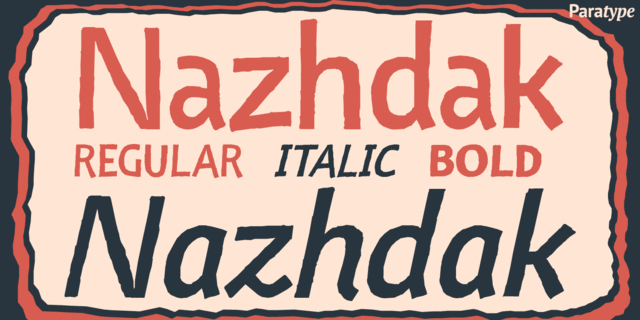
Наждак - рукописный гротеск в трех начертаниях, нарисованный фломастером и впоследствии оцифрованный. Создан под впечатлением от шрифта Эрика ван Блокланда FF Kosmik в 2001 году. Наждак нащупывает границы между регулярным и нерегулярным наборными шрифтами. Несмотря на рваные края и общую расхлябанность, неплохо смотрится в наборе мелким кеглем, а в крупном проявляет свое грубое обаяние в полной мере. Предназначен для набора небольших неформальных текстов и акциденции. Разработан Захаром Ящиным и выпущен ПараТайпом в 2009 году.
Ассоциации c начертанием Nazhdak BoldКачества и характер:
тусовочный, клубный, движняковый, экстремальный, смелый, рискованный, уличный, хулиганский, экспериментальный, опасный, взрывной, студенческий, дерзкий, бандитский, небрежный, кричащий, вернакулярный, грубый, жесткий, брутальный, радикальный